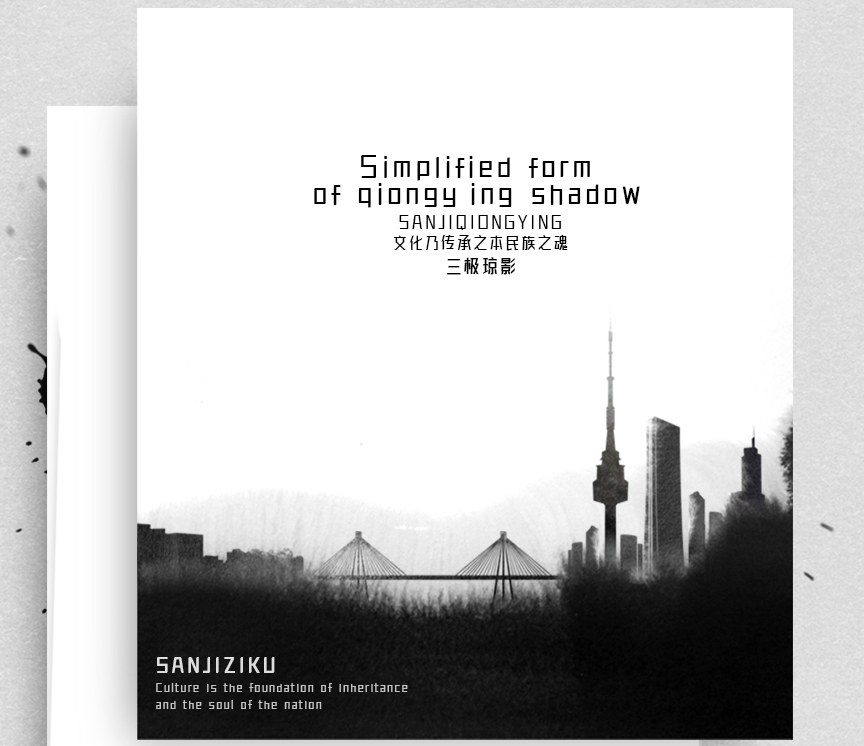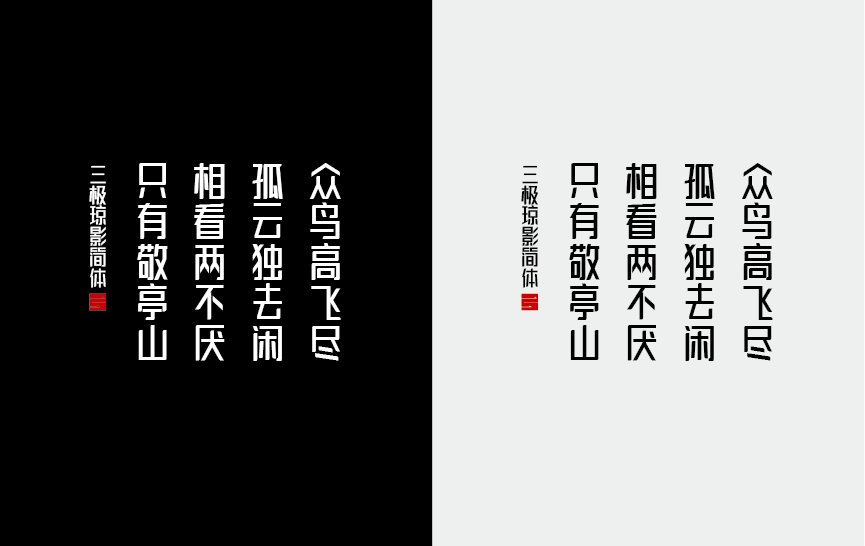
三极虹影简体-粗
文字乃传承之本民族之魂
字体信息
字体名称:
三极虹影简体-粗
设计师:
罗碧霞,庞丽珊
所属分类:
创意字体
字体简介
创作灵感来源于民国时期报纸标题用字,带有老上海画报气息,整体字形略偏瘦长,字体的竖撇点折等都做了相对应的45度圆角处理,笔画与字形二者相结合整体结构灵活不呆板,特别是点的设计,乍一看犹如微风缓缓吹拂着的柳叶,风度翩翩,端庄高雅而标致。适用于复古、做旧、经典主题设计用字。